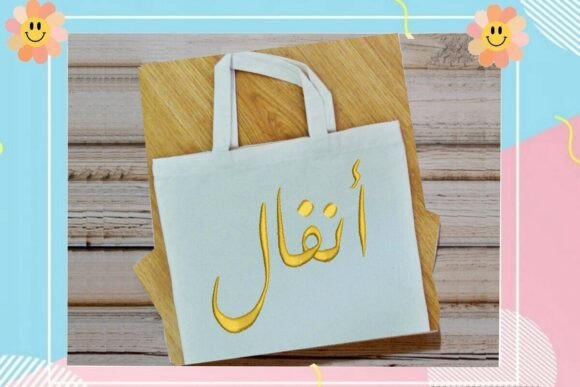
Anfaal Arabic Name
Wenn Sie nach hochwertigen Assets wie Anfaal Arabic Name suchen, ist dieses Premium-Paket eine fantastische Wahl für Ihre kreativen Projekte.
Egal, ob Sie POD-Produkte (Print on Demand), Hochzeitseinladungen oder Social-Media-Grafiken erstellen, Anfaal Arabic Name ist die ideale Wahl.